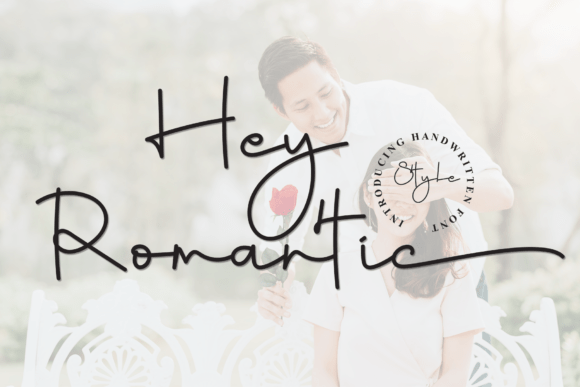
Hey Romantic
หากคุณกำลังมองหาเนื้อหาคุณภาพสูงเช่น Hey Romantic แพ็คเกจพรีเมียมนี้เป็นตัวเลือกที่ยอดเยี่ยมสำหรับโปรเจ็กต์สร้างสรรค์ของคุณ
ไม่ว่าคุณจะสร้างผลิตภัณฑ์ POD (Print on Demand) คำเชิญงานแต่งงาน หรือกราฟิกโซเชียลมีเดีย Hey Romantic ก็เหมาะสมอย่างยิ่ง